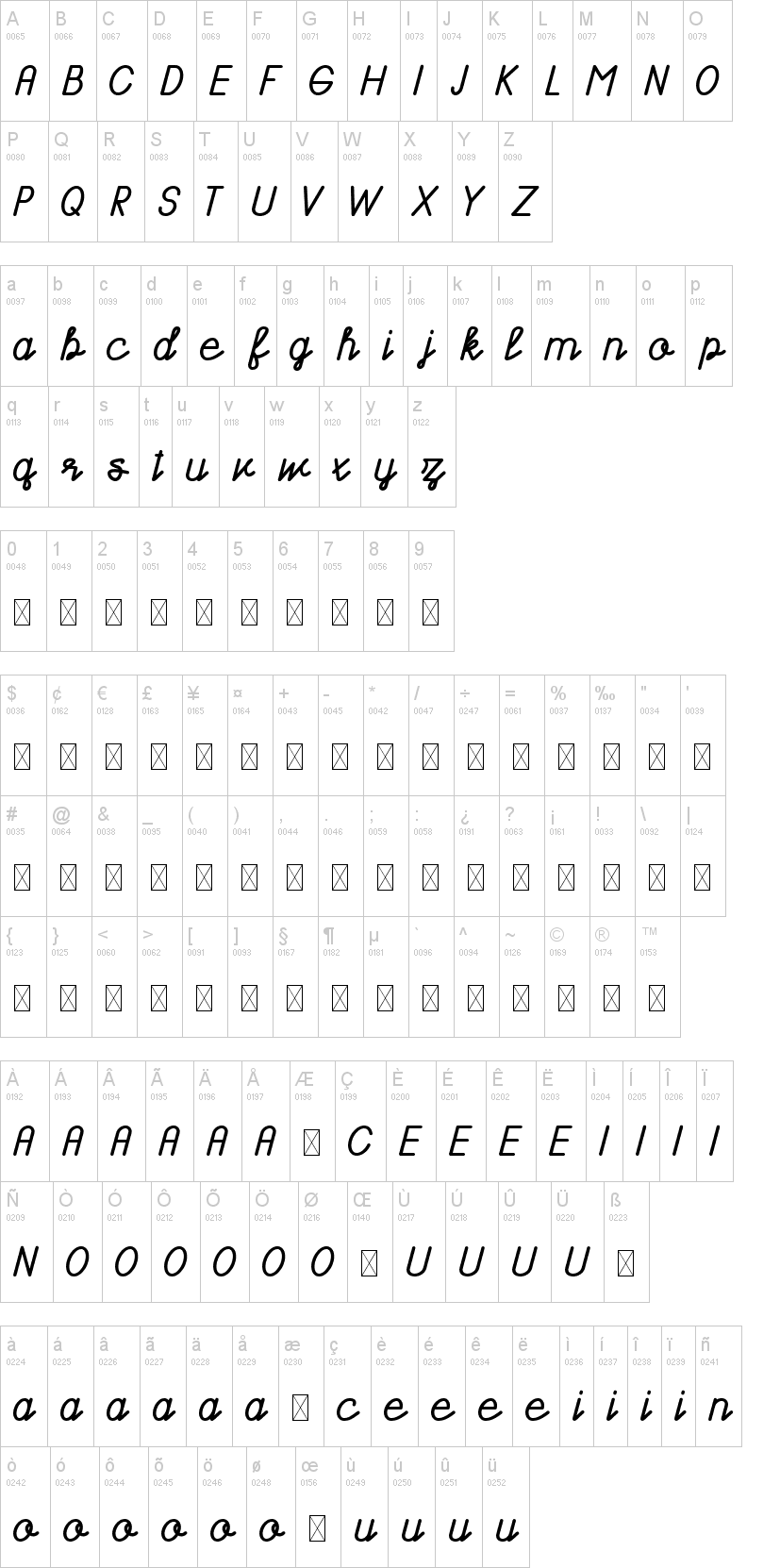
Hamoni
Hamoni 是一款英文字体,由设计师 David Occhino 创作。它是一款简洁、现代、清新的字体,适合用于各种设计项目,特别是网页设计。它的字体设计简洁,易于阅读,拥有丰富的字符集,包括多种字体风格,如细体、粗体、斜体、衬线等,可以满足不同的设计需求。此外,它还支持多种语言,如英语、法语、德语、意大利语、西班牙语等,可以满足不同国家的需求。
Hamoni是一款非常不错的手写艺术字体,具有很好的视觉感,适合于文化类的宣传设计、商业类品牌的广告和产品包装设计以及个性化文字排版等较多场景。
Hamoni字符映射图